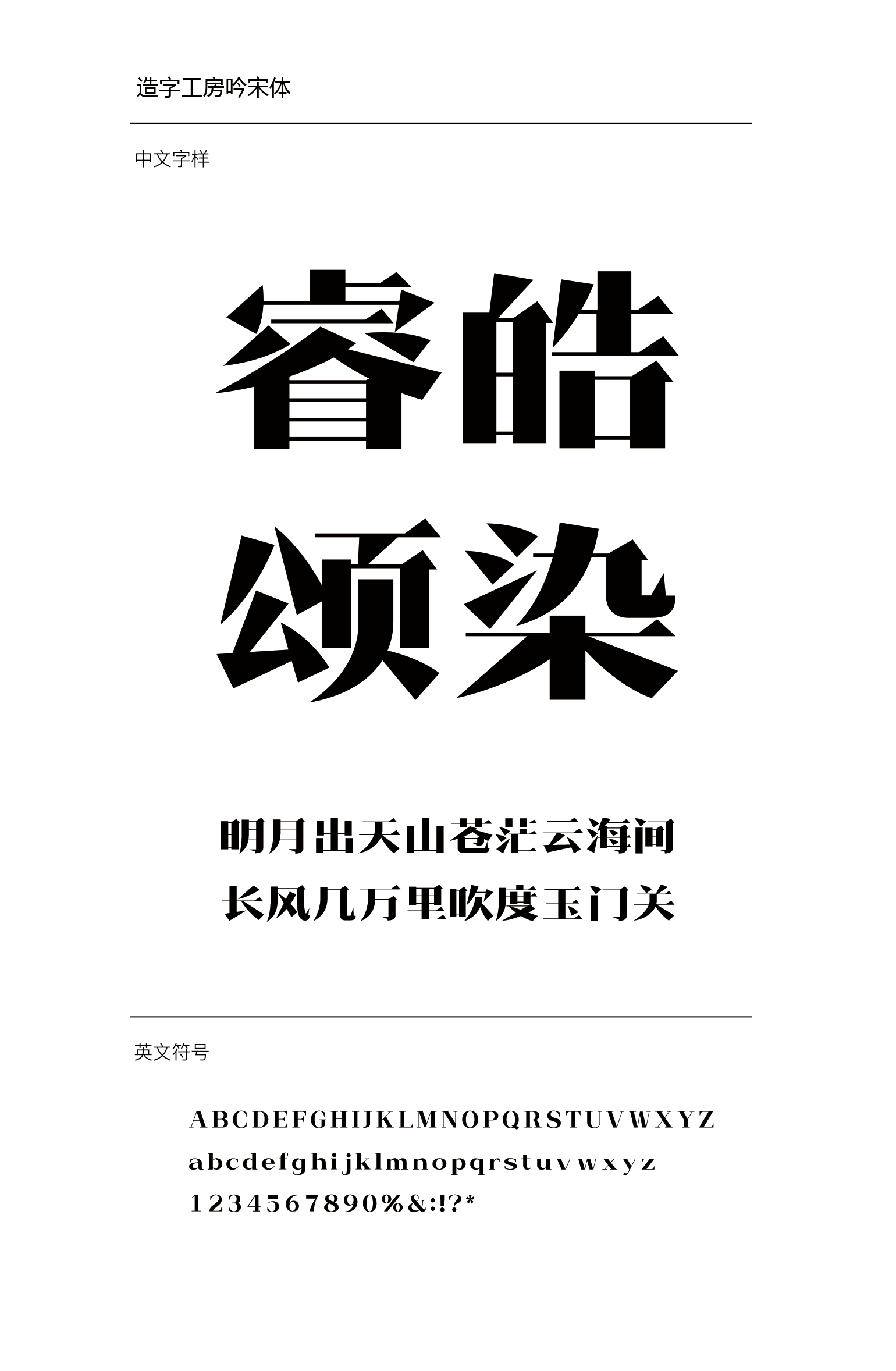
造字工房吟宋
造字工房吟宋设计说明
造字工房吟宋体,字形扁正粗稳、宽博饱满,笔锋端正雄迈而又不失隽秀,一改传统印刷宋体僵直生硬的刻板印象。笔画对比强烈、刚柔相济,结构遒美健秀、规整端庄、收放自如,字形空间结构自然平衡,整套字体庄重严谨,沉稳厚重,极富人文气息。适用于艺术作品、宣传物料包装及个性品牌设计推广等环境。本字体为简体字库,采用OpenType/CID格式,Adobe-GB1-5编码。 基于中华人民共和国GB2312-80字符集标准,另按需添加101个汉字。共收容字数6864CJK汉字,ASCII常用字符100 个。